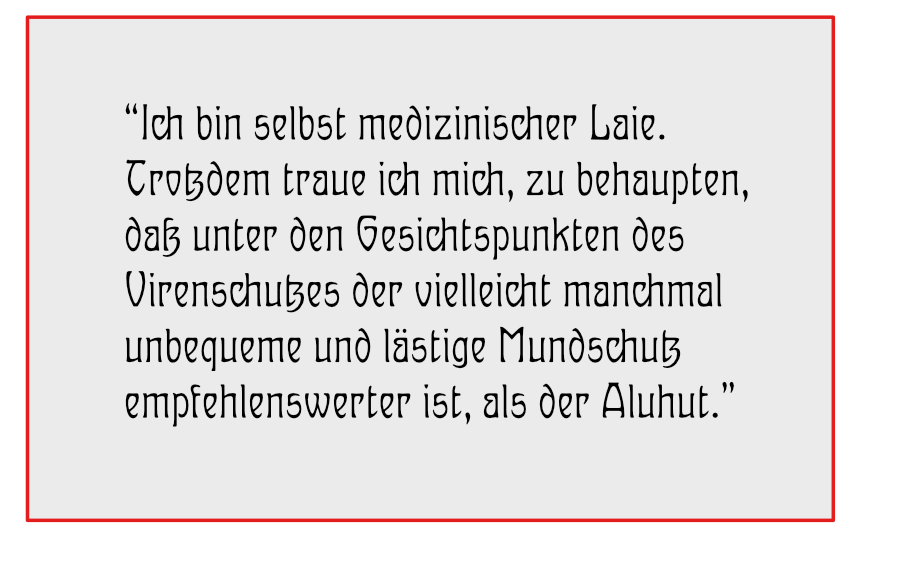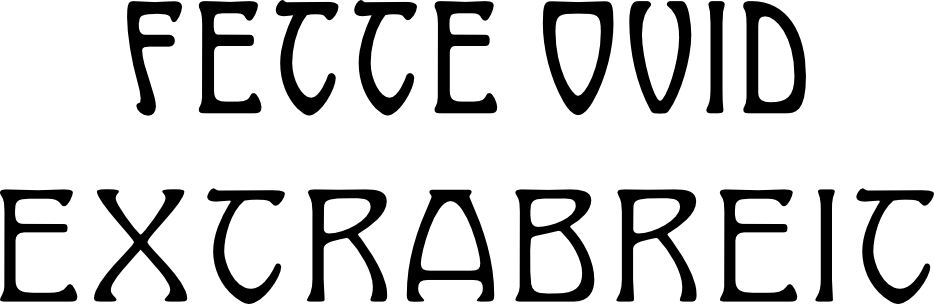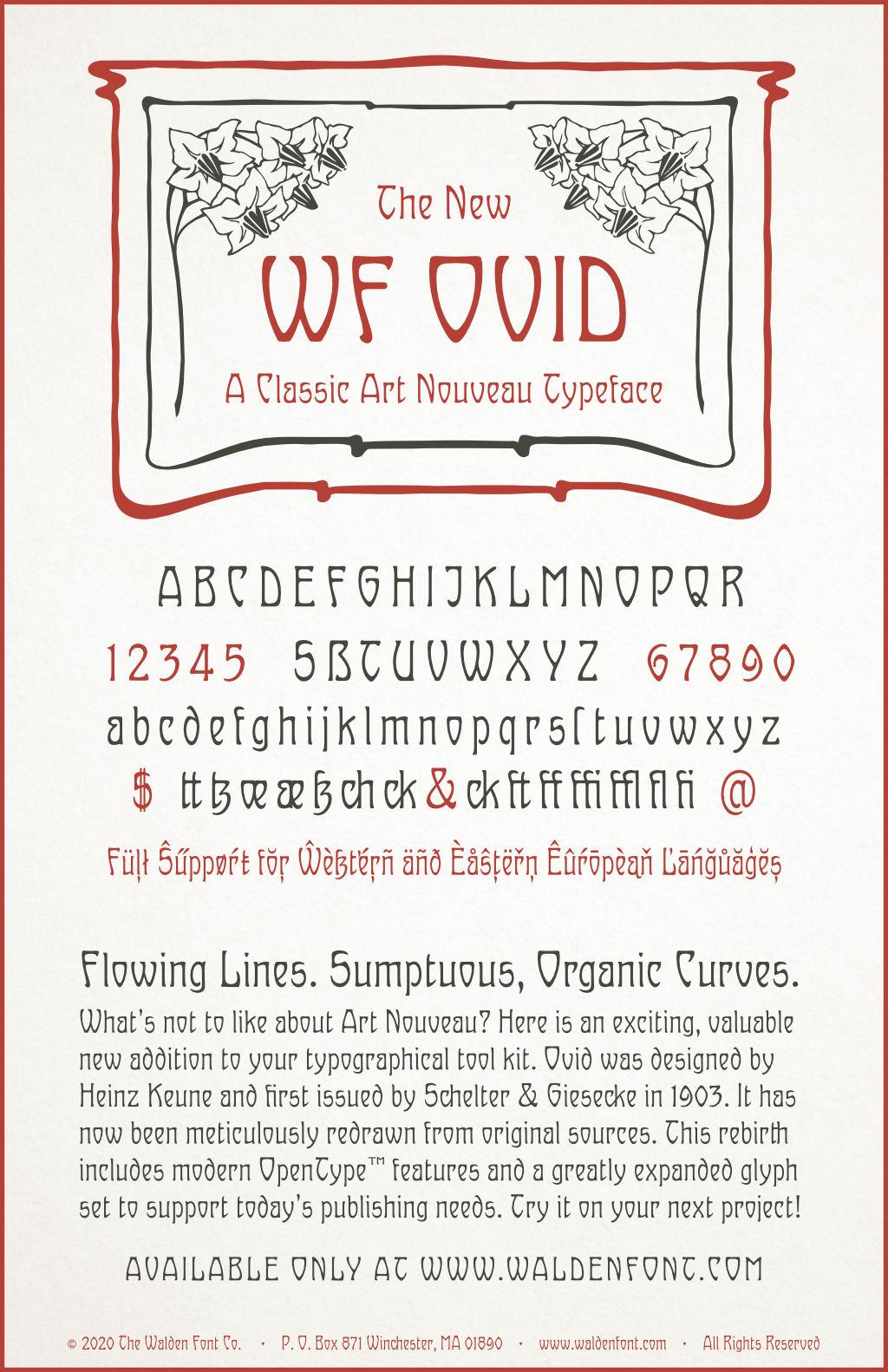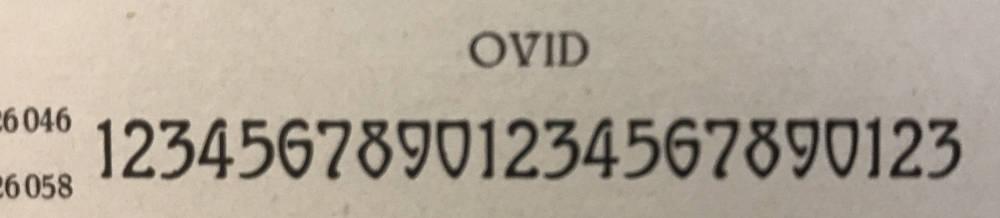
Jugendstil, die Achte: Ovid
Hmmm...mir gefällt die hutzelige Neun irgendwie. Ich habe Angst, eine konservativere Version wird zu langweilig. Mir ist schon die Zwei viel zu Vanilla (Sorry, Phoibos)
Die Null könnte oben vielleicht etwas spitzer zulaufen oder sich sonst irgendwie etwas besser vom O unterscheiden? Die 2 wäre mir auch noch einen Tick zu »symmetrisch« (oben/unten). Aber insgesamt sehr schön nachempfunden, finde ich.
... warum man zugenommen hat und warum man doch mal 'ne andere 9 probieren sollte ;-) Einen Vergleich fände ich auch ich reizvoll ... *schokohol*
Genau dies was Thomas zur 9 sagte, war auch mein erster Gedanke, als Thomas' Antwort noch unter meinem Bildschirm steckte. Die 9 also quasi aus dem horizontal gespiegelten C gebaut, so würde ich da heran gehen.
Letzthin gab es so viel zu tun, daß ich kaum ins Forum schauen konnte. Die mir vergönnte Freizeit verprasste ich mit der Ovid. Jetzt ist sie soweit fertig.
Ich bin damit sehr zufrieden. Sie hat fast etwas klassisch-aristokratisches an sich. Da vergißt man gänzlich, daß sie sich mit "Covid" reimt.
Übrigens habe ich noch ein paar Ligaturen für th, ch, ck, usw. eingeschmuggelt.
Ist eine wunderschöne Alzernative zur praktisch totgerittenen Arnold Böcklin.
Wollte ich ein Gasthaus eröffnen,wäre die wohl auf meinem Schild.
Aber ich mochte den Jugendstil immer schon gerne, ald meine Mutter noch mit Antiquitäten handelte...
Dafür finde ich sie zu mager. Gäbe es die Möglichkeit einer (halb)fetten Variante?
Gibt's das ʒ in tʒ und ſʒ eigentlich auch einʒeln?
Kein Geld zum Schriftenkauf vorhanden, daher fragste den falschen, aber ich könnte mir vorstellen, dass diejenigen, die tʒ und ſʒ verwenden, aus Einheitlichkeit auch gerne das ʒ in dieser Variante hätten ...
[Wer würde ʒ] verwenden?
Anbieter von Piʒʒa? :-? (Wir 🇺‍🇸 kennen das ja von  unzähligen , oft [aber nicht immer] handschritftartigen, Beschilderungen.)
Beim Googeln nach Beispielen bin ich übrigens auch auf dieses gestoßen:
Oh Schnitzel, was hast Du da angestellt? Jetzt arbeite ich mich ungewollt in Variable Fonts ein :twisted:
Hätt ich die Ursprungsversion nicht gesehen ich würd auch daran gefallen finden.
Mit dem Charme der  native Ovid könnnen sie aber nicht mithalten. was aber keine Rüge sein soll an weitere Versionen, vielmehr eine Huldigung der Ursprungsversion.
Allerdings hätte ich mit mehr Strichkontrast gerechnet 🤔
Nach all dem habe ich heute eine Probe erhalten, die alle Ziffern darstellt. Meine gefallen mir zwar besser, aber was soll's, ich mache sie noch einmal :-?